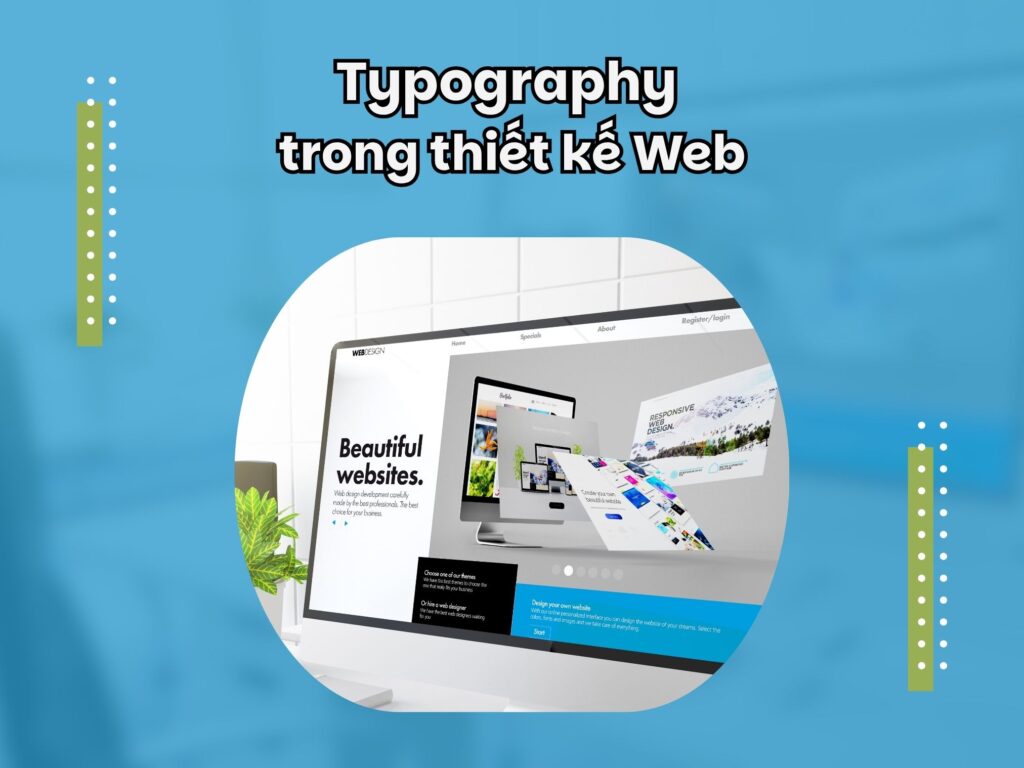
Bí quyết ứng dụng Typography trong thiết kế Web chuyên nghiệp
Để xây dựng một website thu hút, chuyên nghiệp và tạo ấn tượng mạnh mẽ với người dùng, không thể chỉ dựa vào giao diện bắt mắt. Một trang web hiệu quả là sự kết hợp tinh tế giữa thẩm mỹ, bố cục hợp lý, trải nghiệm người dùng mượt mà và đặc biệt là sự đồng nhất trong từng chi tiết thiết kế. Trong đó, typography – nghệ thuật sử dụng chữ – đóng vai trò cốt lõi, không chỉ nâng cao khả năng đọc hiểu mà còn định hình phong cách thương hiệu trên môi trường số. Vậy typography trong thiết kế web được ứng dụng ra sao, và đâu là những nguyên tắc cần lưu ý? Hãy cùng Fontchuan.com khám phá trong nội dung chi tiết dưới đây.
Typography – Nền tảng thị giác & Trải nghiệm người dùng trên Website
Định nghĩa Typography trong bối cảnh thiết kế web
Typography là nghệ thuật sắp xếp và thiết kế chữ viết nhằm truyền tải thông điệp một cách hiệu quả và có tính thẩm mỹ cao. Khái niệm này bao gồm nhiều yếu tố quan trọng như lựa chọn kiểu chữ (font chữ), màu sắc, kích thước, và khoảng cách giữa các ký tự. Mục đích chính của typography là đảm bảo văn bản hiển thị rõ ràng, dễ đọc và thu hút người dùng.
Định nghĩa Typography trong bối cảnh thiết kế web
Trong lĩnh vực thiết kế web, typography đóng vai trò đặc biệt then chốt. Điều này là do hơn 95% thông tin được trình bày trên các website đều dưới dạng văn bản. Do đó, typography không chỉ là một yếu tố thiết kế đơn thuần mà còn là xương sống cơ bản của giao tiếp kỹ thuật số. Một hệ thống typography được thiết kế kém có thể dẫn đến việc truyền tải thông điệp không hiệu quả, bất kể chất lượng nội dung gốc. Việc đầu tư vào typography chất lượng cao đồng nghĩa với việc đầu tư vào khả năng giao tiếp rõ ràng và hiệu quả, một yếu tố tối quan trọng đối với sự thành công của bất kỳ trang web nào.
Vai trò quan trọng của Typography trong website
• Tối ưu khả năng đọc hiểu: Kích thước, kiểu chữ, khoảng cách dòng… ảnh hưởng trực tiếp đến trải nghiệm đọc của người dùng. Typography tốt giúp nội dung dễ tiếp cận, ngược lại có thể gây khó chịu và giảm khả năng tiếp nhận.
• Xây dựng nhận diện thương hiệu: Font chữ là một phần của ngôn ngữ thương hiệu. Việc lựa chọn và sử dụng font phù hợp sẽ tạo ấn tượng thị giác, giúp thương hiệu trở nên nổi bật và dễ ghi nhớ.
• Tạo cảm xúc và sự tương tác: Typography còn truyền tải cảm xúc – nghiêm túc, hiện đại hay vui tươi – thông qua phong cách chữ và bố cục. Nó định hình không khí tổng thể của website.
• Tăng hiệu quả UX/UI: Typography tốt giúp điều hướng mắt người đọc, hỗ trợ cấu trúc nội dung rõ ràng và tăng tính trực quan, từ đó cải thiện tỷ lệ tương tác và giữ chân người dùng.
Typography trong thiết kế web không chỉ dừng lại ở việc chọn font hay căn chỉnh chữ cho đẹp mắt, mà còn liên quan đến cách chữ truyền tải thông tin một cách hiệu quả. Để hiểu sâu hơn những nguyên tắc đang được áp dụng trên giao diện web hiện đại, chúng ta cần bắt đầu từ nền tảng cốt lõi nhất: tìm hiểu về typo là gì và vai trò thực sự của nó trong thiết kế.
Nguyên tắc vàng ứng dụng typography trong thiết kế web
Typography không chỉ là yếu tố thị giác mà còn ảnh hưởng trực tiếp đến trải nghiệm người dùng, khả năng tiếp cận, tốc độ tải trang và hiệu quả SEO. Phần này tổng hợp các nguyên tắc cốt lõi giúp tối ưu typography trong thiết kế web hiện đại.
Lựa chọn font chữ thông minh
Việc chọn font cần được cân nhắc kỹ về cả thẩm mỹ lẫn hiệu năng kỹ thuật:
• Giới hạn số lượng font: Chỉ nên sử dụng tối đa 2- 3 họ font cho toàn bộ website để đảm bảo tính nhất quán, dễ quản lý và tránh làm nặng trang.
• Ưu tiên font web-safe: Các font như Arial, Georgia, hoặc từ Google Fonts giúp đảm bảo khả năng hiển thị đồng đều trên nhiều thiết bị, tăng tốc độ tải trang.
• Chọn font dễ đọc, linh hoạt: Font cần hiển thị tốt ở nhiều kích cỡ và độ phân giải, đặc biệt trên thiết bị di động. Tránh font viết tay, font trang trí rối rắm hoặc có ký tự khó phân biệt (như “rn” dễ nhầm thành “m”).
• Đảm bảo độ rõ ràng: Kiểm tra khả năng phân biệt giữa các ký tự gần giống để tránh gây hiểu nhầm cho người dùng, đặc biệt trong phần thân bài hoặc nội dung dài.
Một lựa chọn font thông minh không chỉ nâng cao trải nghiệm người dùng mà còn giúp cải thiện thời gian tải trang, tăng tính tương thích và hỗ trợ SEO on-page hiệu quả.
Tối ưu khả năng đọc (Readability) và tính rõ ràng (Legibility)
• Legibility là mức độ rõ ràng của từng ký tự trong typeface, do nhà thiết kế chữ quyết định. Typeface có x-height lớn, counters mở, hình dáng chữ cân đối sẽ tăng tính legibility.
• Readability là cách văn bản được trình bày – thuộc phạm vi kiểm soát của nhà thiết kế web – bao gồm cỡ chữ, leading, tracking, độ dài dòng và khoảng trắng.
Một font có thể rõ ràng nhưng trình bày kém sẽ khó đọc; ngược lại, layout dễ đọc cũng không thể cứu được một typeface kém chất lượng. Vì vậy, legibility là nền tảng, readability là cách triển khai – cả hai phải được tối ưu đồng thời.
Quản lý khoảng cách và bố cục
Khoảng cách là yếu tố quyết định trực tiếp đến cảm giác “thoáng” và mức độ tập trung của người đọc: